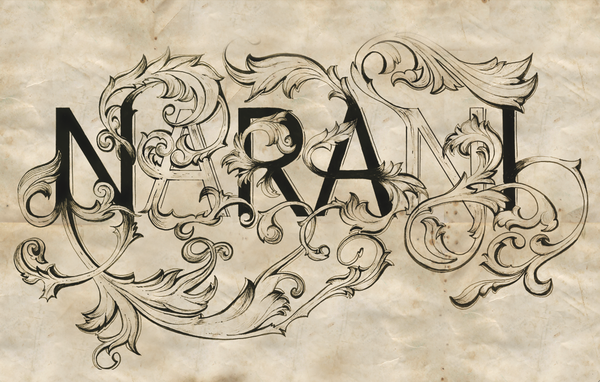
Narani Kannan
Por mais que tenha se tornado algo muito lugar comum, esse estilo de tratamento tipográfico repleto de ornamentos ainda me interessa muito.